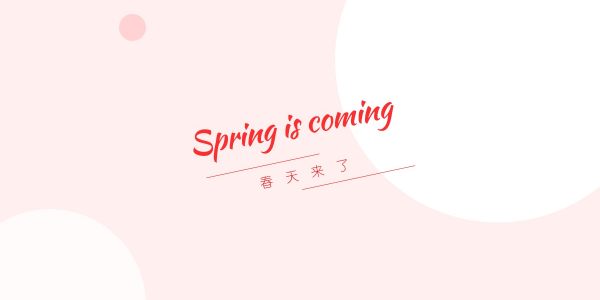
中英文如何搭配最好看?
{{tag.name}}虽说中国不是英语国家,但是在现代平面设计当中,很多时候也会涉及到对英文的使用。尽管大部分时候,英文在版式中出现的作用不是为了传达信息,而是为了增加装饰,平衡排版等,但正因如此,我们更应该了解英文字型的特征并加以运用,让中文传达的信息更精彩。
双语化始终是一个不可避免之势,我们在接触的部分客户其实已经选择采用双语来传递信息,因此,对于英文的掌握有一定的要求。最近,我正在看小林章的《欧文字体》,因此结合本书的部分内容,增加我对中英文搭配组合字型选用问题的学习记录写了这篇文章。
罗马体/衬线体
1. 选用合适的英文
罗马体/衬线体指的是笔画前端处有着爪状或线状的「衬线」的字体,因为这种样式的大写字母完成于古罗马,所以被称为罗马体,也同时被成为衬线体或者饰线体。
罗马体在英文排版中使用很广泛,在和中文搭配时,尤其是宋体、仿宋等字形,都能很好地进行呼应。当然,罗马体也有很多可选的字体,茫茫字海中挑选字体的关键还是要看字形的笔画特征。
比如下面的案例中,中文的部分我采用的是「浙江民间书刻体」,这款字体的特征是:
手工痕迹明显
保留了宋体的字形特征(横细竖粗)
带有古风
所以在选择英文作为搭配的时候,也同样选用「Roman SD」这款字体与之搭配,可以看到这款英文字体的特征也十分明显:
手工痕迹明显
横竖笔画比例和中文字体类似
带有古风
可以说这两款中英文就是十分相近的。如果是实际运用时,我建议大家再从细节入手,把这两款字形再调得更接近一点(比如把英文的部分的粗线部分再加粗)。相比来看,右边如果将英文换成无衬线体,那么彼此就显得不太相容。除非是故意表现这种比较「相撞」的感觉,否则我会弃用右边的组合。
但是,并不是所有中英文搭配都必须符合以「字型相同」的组合原则,最重要的是学会抓住饰线的视觉特征。
2. 抓住饰线的视觉特征
饰线是笔画起始端的装饰,其实在从前文字是被刻在石头、木头、动物骨头等表面,本来是书写工具书写时留下的痕迹,并没有特意美化之用,只是越往后发展,它的美化功能越突出。
饰线也分为几种大类,根据文明发展的过程,早期具有书写痕迹的罗马体被称为「旧式罗马体」,18 世纪以后所流行的直线式的衬线字体为「现代罗马体」。
但旧式罗马体其实并不如字面有「老旧过时」之意,在 21 世纪的今日,大多的书籍内文排版都还是以「旧式罗马体」为主。
此外书中另一部分提到的「曲饰线体」,也有的地方称之为花饰线体,指的是在文字起笔处和收笔处被特别拉长的装饰曲线。
饰线的特征不同,其可与之搭配的中文也就不同,比如同为旧式罗马饰线体,下面两款搭配,中文为仿宋,而与此相搭配的英文,左边为旧式罗马饰线体「Constantia」,它看上去持重沉稳,中英文之间彼此的笔画特征是比较接近的,收尾的端口皆为略小的方口。
而右边的英文是「Cinzel Decorative」,它看上去很优雅,具有古典风范,但是和中文的笔画收尾风格不太相似。
也许有部分人会更倾向选择左边的搭配,但是我却是站右边的搭配的。
3. 对比的力量
为什么我要拥护右边的搭配呢?这里我们要谈到对比。对比就是我们这个世界得以运行的法则之一,一切感受都是从对比中产生的,比如美与丑、善与恶、黑与白……有了这个思维基础,那么在视觉中,当我们想要制造某种效果,那么你就要制造出这个效果的反面特征。
在涉及到美观度而言,「Cinzel Decorative」这款字体看上去纤细又典雅,而且它的密度比较小,因为英文字腔比较大,所以中和了仿宋体中文部分的字体内部的高密度问题(比如参考「烟」字右边的「因」,其中所留空白并不多),这样就能形成焦点以中文为主,英文为辅,相辅相成的视觉感受。
而且,在字型的性格特征上来看,「Cinzel Decorative」的精致典雅又能和仿宋的古朴感相对比,这两种感受的交织,可以说是一种巧妙的混搭。但是混搭并非乱搭,大家可以看看右边,我用了另一个英文字体「Abril Fatface」,属于现代罗马体,因此在和仿宋搭配就显得不伦不类,似乎彼此并不关联,因为它的现代感让它本身无法和仿宋融为一体。而它本身字体的密度又很高,和仿宋类似的黑度,让整体看起来没有焦点。
由此可以窥见,中英文搭配不仅要涉及到字体、字型特征,还要兼顾到字体的黑度,文字本身(比如这里的「烟灰」二字,如果换成其他文字,未必会是这样的选择)。
无衬线体
无衬线体就是没有衬线的字体。在现代商业中,由于其简练的外观,越来越多地被采用。作为活字登场于 19 世纪前半,被普及使用则是 20 世纪之后的事了。
如果要说能与无衬线体相协调的中文字体,那无疑就是我们常见的黑体字,黑体其实也就是中文界的无衬线体。下面的中文所使用的是「思源黑体」,左边的英文所采用就是无衬线体「Nexa」,而右边则采用的是衬线体「Javanese Text」。
可以看出左边的组合更能传递出某种干练明晰的感觉,而右边则略有些退缩。黑体和无衬线体的搭配,更有助于信息传达的直接性。
除了比较传统的黑体能搭配无衬线体的英文,其他的黑体一样可以搭配出不错的效果。中文字体在黑体基础上也会有很多变体,这些笔画上的不同的表现,需要找寻的依然是笔画特征的协调性。
比如下面的案例中,中文采用的风格比较明显的黑体字,字形整体上是以圆角矩形为基础框架,英文当然也采用无衬线体,但是无衬线体也有无数的笔画风格,这里采用中黑粗的无衬线体是更好的选择,比起细体,这样的组合更「明确」,细体则显得中气不足。
1. 字体的音效
中文黑体字在平面设计中类似一种「高声喊话」的视觉效果,并且笔画越粗,其「声音」就越大。英文的无衬线体也有着现代性、直观性的特征,因此,如果要很明确传达信息,比如商业促销宣传等海报设计中,无衬线体无疑是非常适合的。
而细体通常用于比较精致、优雅的平面当中,更具有女性特征。它虽然传达效果没有那么迅捷,但是却能表现一种时尚现代感,是稍微缓和的黑体。可以参见下面的字体运用:
在这里我分别运用的字体是「josefin sans」以及「Nue」,Josefin 是我一直喜欢的细体,几何感造型很强烈。而 Nne 的设计感非常适合用在比较独立的场合,它是能量很大的字体,所以与之搭配的时候,尽量让它的设计感突出,周围不要再增加多余的装饰。
在主张「轻」风格的设计中,细体更能表现出轻的质感。
原书中小林章还举了意大利体,但现在意大利体已经发展成为斜体,在很多的英文字体中都有斜体的选择。意大利体最早还是一种手写体。
所以,我们这里会谈到手写体。除了正文排版,在很多时候,运用手写体英文,让画面变得更活泼,手写的痕迹会增加更多的趣味性。
在原书中,小林章是这样介绍的:
我们在这里讲的手写体和草书体不是一个范畴的概念,手写体显然涵盖的范围更大。
以上四种字体(「MV Boli」、「Lobster」、「Kaushan Script」、「Alex Brush」 )都是手写体,但是它们的表现效果差异很大,所以要说手写体的风格,几乎就是一人一个风格,这和每个人笔迹都不同是一个道理。
如果把手写体英文和中文做组合,我的建议有下面几点:
感受书写的性格
每个人写出的字都不一样,表现着个人不同的性格特点,手写体就是有这样的独特魅力,所以感受你所用手写体的性格感觉来搭配整体画面。
突出书写的独特表现
在运用书写体时,尽量把它当作一种氛围装饰来使用,而且是必定要是一个主角。由于它极大的自由感和独特性,如果也和其他的字体一起使用,没有做突出,甚至被埋没,那就不如不要选用手写体。
保持一个书写风格
如果画面中出现两种手写风格,不但画面看上去繁杂,而且显得太吵吵闹闹,如果不是做大卖场的广告,我想这样的视觉传达是不合格的。选用中文的时候也尽量选择性格不太突出的中性字体。
以上这个设计中,我运用了「Kaushan Script」这个手写体,这是我比较喜欢的书写风格,收尾有锋,且造型简洁,笔画柔和,但也有倾斜带来的动感效果,看上去干净利落。与此搭配的中文我选用的是比较中规中矩的幼圆,看上去性格柔和,比较像一个配角。线条在这里营造动态效果和优雅感。整体感觉明快。字体整体都做了略微的旋转,这样就能更好诠释当下的氛围。
手写体的氛围本身就是活泼明快的,于是画面也可以往这个方向靠拢。
小结
除了以上所讲到的大类,还有一些小类的英文字体。
比如哥特体其实也是欧文书写体的一种,但风格迥异,在中国的设计中几乎不怎么用到。但由于历史的沉淀,变成一种非常独特的字体风格。
我们虽然是解析小林章对英文字体的类别划分,但在此我和大家又分享了一些中英文搭配的技巧和要点。平面设计中中英双语使用的情况会越来越多,因此对英文的了解会带我们进一步加速这一结合。